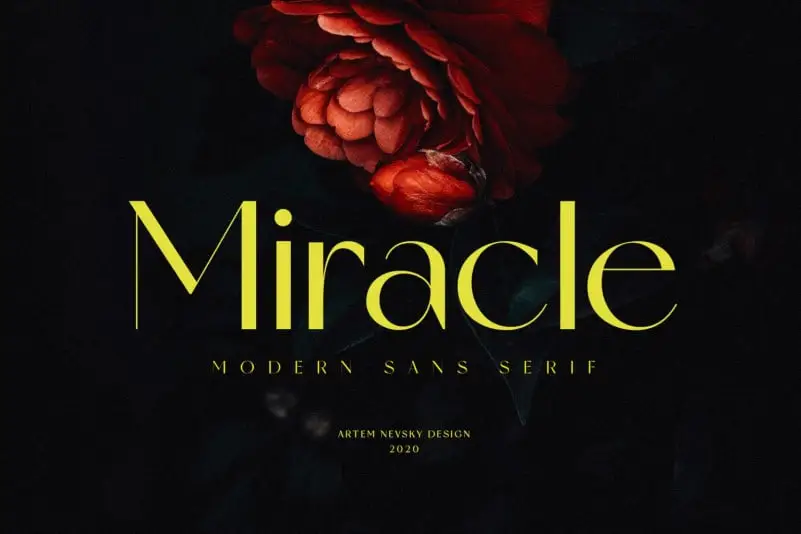
Miracle Sans Serif Font – Download Grátis
A Miracle Sans Serif Font é uma nova tipografia sans serif criada pelo nevsky type com ares elegantes e contemporâneos. Ela se destaca pela sua versão moderna e sofisticada, tornando-a perfeita para aplicações como design de web, identidade visual, arte gráfica, selos ou qualquer outro tipo de trabalho que exija uma tipografia com um estilo moderno. Seu formato simples e limpo encaixa-se perfeitamente em ambientes digitais, garantindo a leitura precisa e clara para todos os usuários. A Miracle Sans Serif é o ideal para quem busca um design clean e contemporâneo sem perder a elegância que tanto valorizamos.